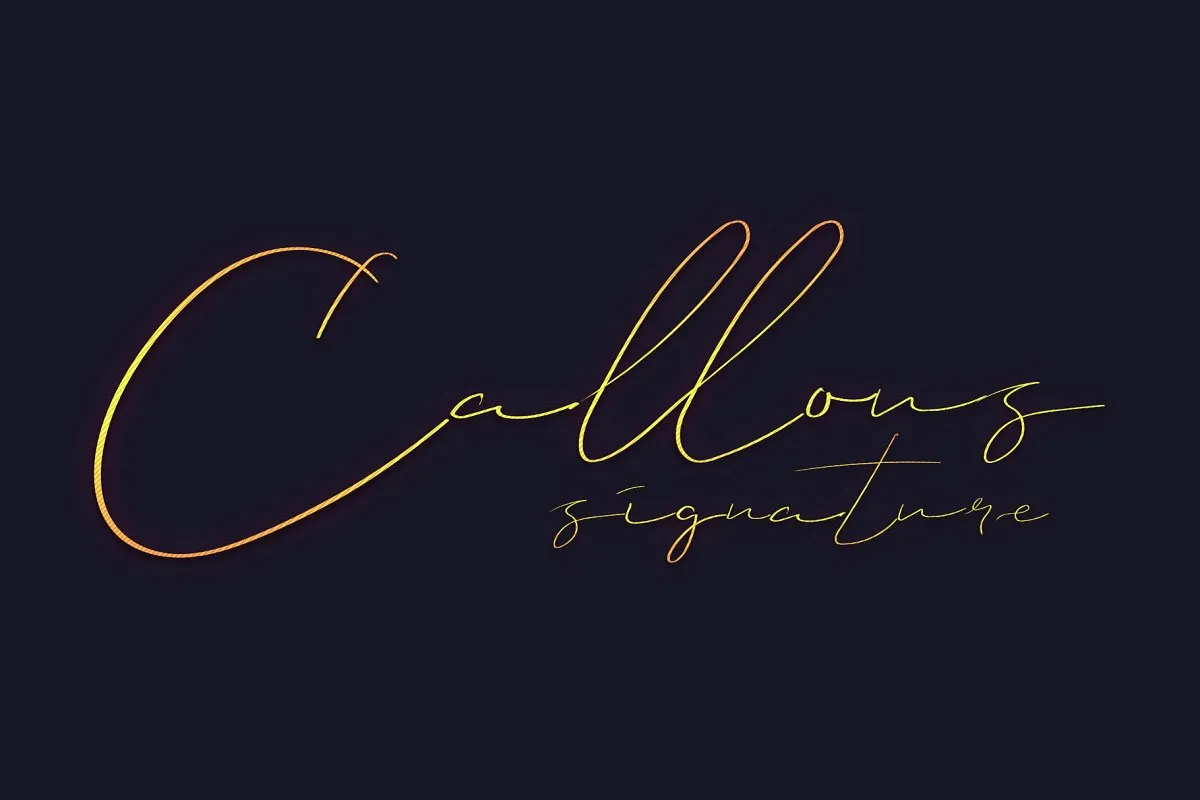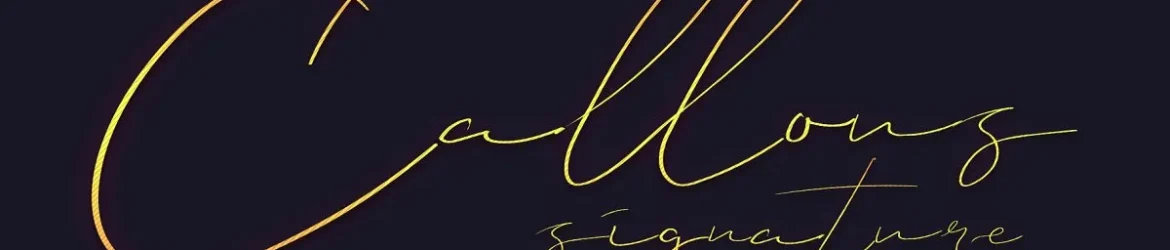
Callous Signature Font – Download Grátis
A Callous Font é uma nova adição no catálogo das fontes de签字体 pelo Gumacreative. Esta é outra fonte de script que enriquece sua paleta de opções, perfeitamente adaptada para estilos como logotipos, banners, posters ou até mesmo assinaturas. Essa fonte original de escrita manual traz um toque autêntico aos seus designs. Concebida para designers entusiastas e amantes da arte gráfica, a Callous Font oferece uma experiência única no universo das fuentes manuscritas, proporcionando personalidade e profundidade a qualquer projeto. Seja você um designer de novos logotipos ou criador de projetos visuais impactantes, a Callous é sua melhor aliada para dar vida à sua arte. Não hesite em experimentá-la; ela certamente se encaixa perfeitamente no seu estilo!